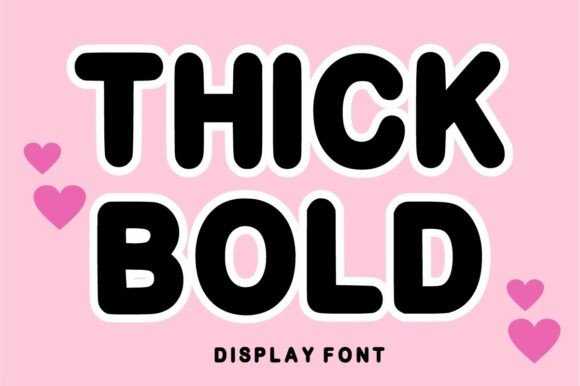
Thick Bold
Thick Bold – A Fonte Que Transforma Qualquer Mensagem em Impacto Visual
Se você está em busca de uma tipografia que una massa e aproximação, a Thick Bold é a escolha certeira. Este display font apresenta formas arredondadas ultra‑pesadas, garantindo máxima presença sem pontas agressivas. Ideal para outdoors, manchetes de redes sociais e estampas de roupas, a Thick Bold combina legibilidade impecável com personalidade marcante.
Por que a Thick Bold se destaca?
- Peso substancial – funciona como âncora visual, estabilizando layouts caóticos.
- Arredondamento amigável – elimina a sensação de dureza, tornando a comunicação mais acolhedora.
- Legibilidade superior – mesmo em grandes distâncias ou tamanhos reduzidos, as letras permanecem claras.
- Versatilidade de uso – perfeita para billboards, posts no Instagram, capas de YouTube e peças de vestuário.
- Combinação cromática – destaca-se ainda mais ao ser pareada com tons pastel suaves ou detalhes em coração, como mostrado nas pré‑visualizações.
Como aplicar a Thick Bold na sua marca
Use a Thick Bold como headline principal e complemente-a com fontes mais leves nos textos de apoio. Essa hierarquia cria contraste visual, enfatizando a mensagem central sem sobrecarregar o leitor. Experimente combinar a fonte com cores pastel, gradients ou elementos gráficos delicados para um visual confiante, amigável e inesquecível em mercados saturados.
Em resumo, a Thick Bold oferece o equilíbrio perfeito entre força visual e simpatia, garantindo que sua mensagem seja vista, compreendida e, sobretudo, lembrada. Não deixe sua comunicação passar despercebida – dê a ela a presença que merece com a Thick Bold.